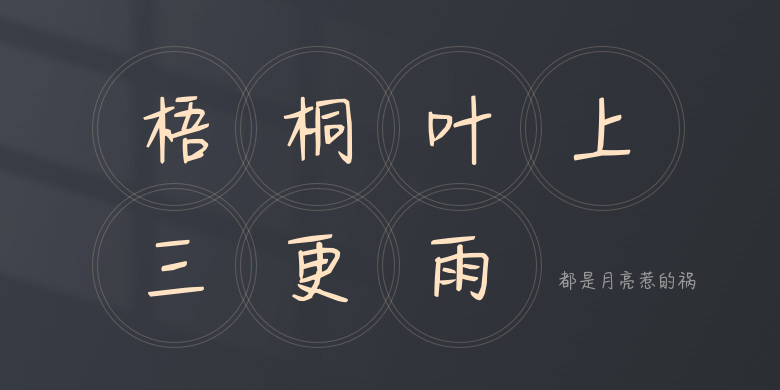
都是月亮惹的祸
都是月亮惹的祸,这款字体结构工整、笔画清晰,兼顾美观与易读性,适用于标题、正文、海报、包装、LOGO 等多种场景。字形优雅稳定,风格百搭耐看,适配日常排版与创意设计,让文字呈现更舒适、更具质感。都是月亮惹的祸一笔一画,皆是细节,以均衡的比例、流畅的线条打造舒适视觉体验,字形端正大气,风格简约现代。无论是商业设计、品牌宣传还是日常排版,都能轻松驾驭,让文字更有格调与力量。都是月亮惹的祸字体下载。